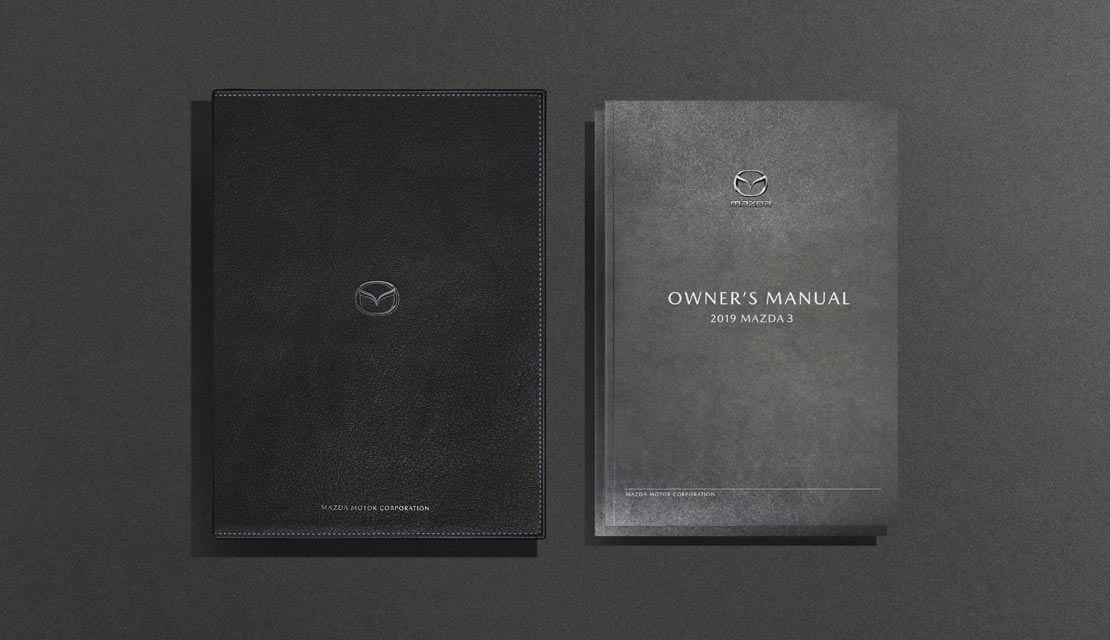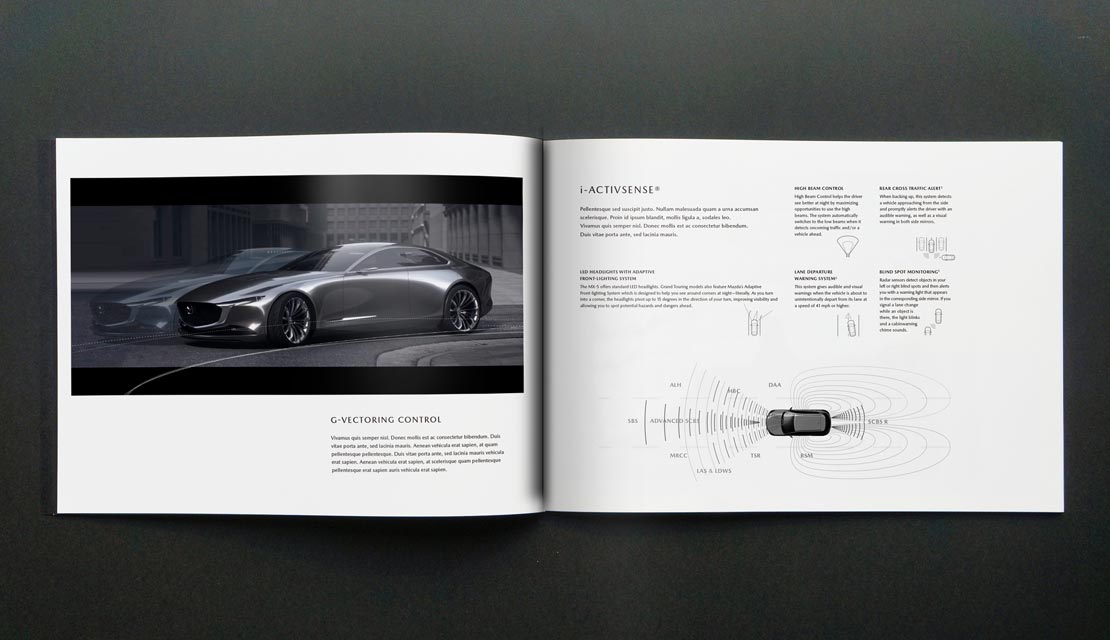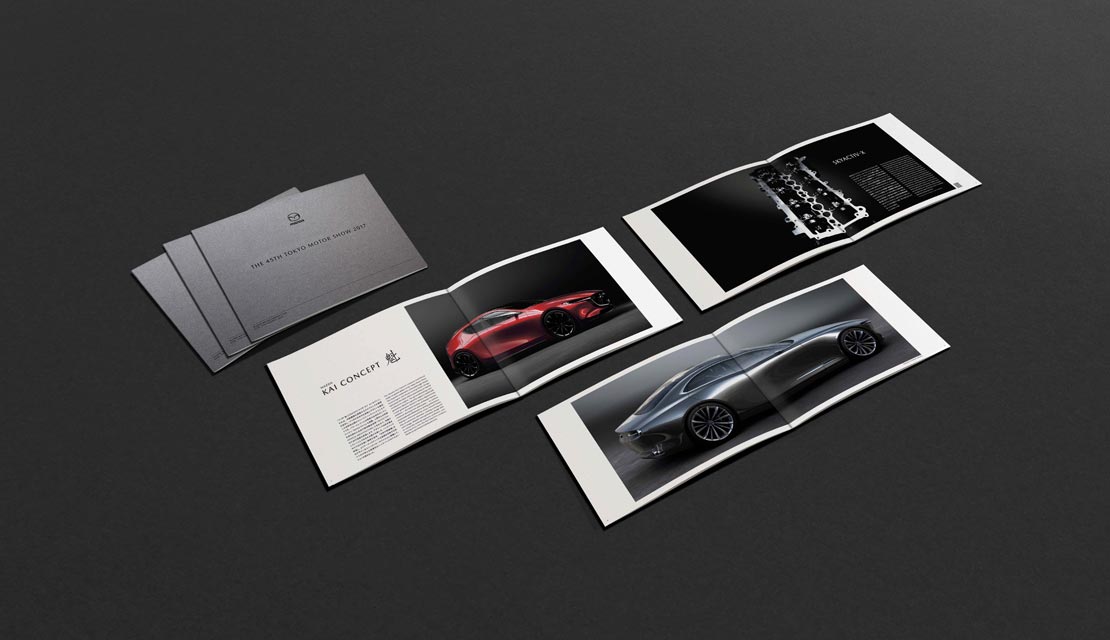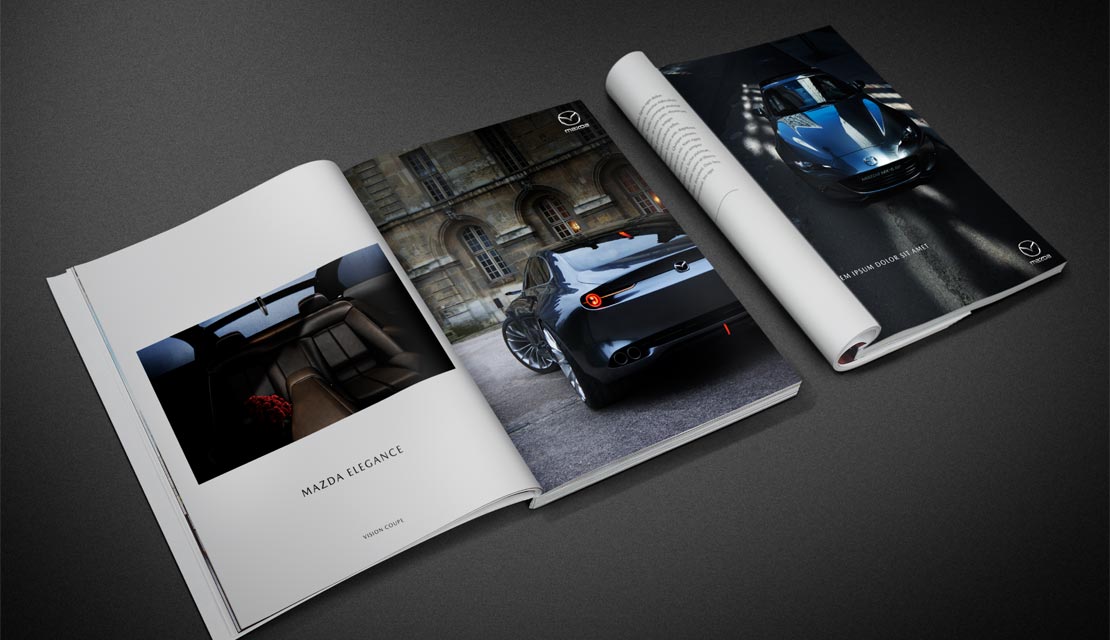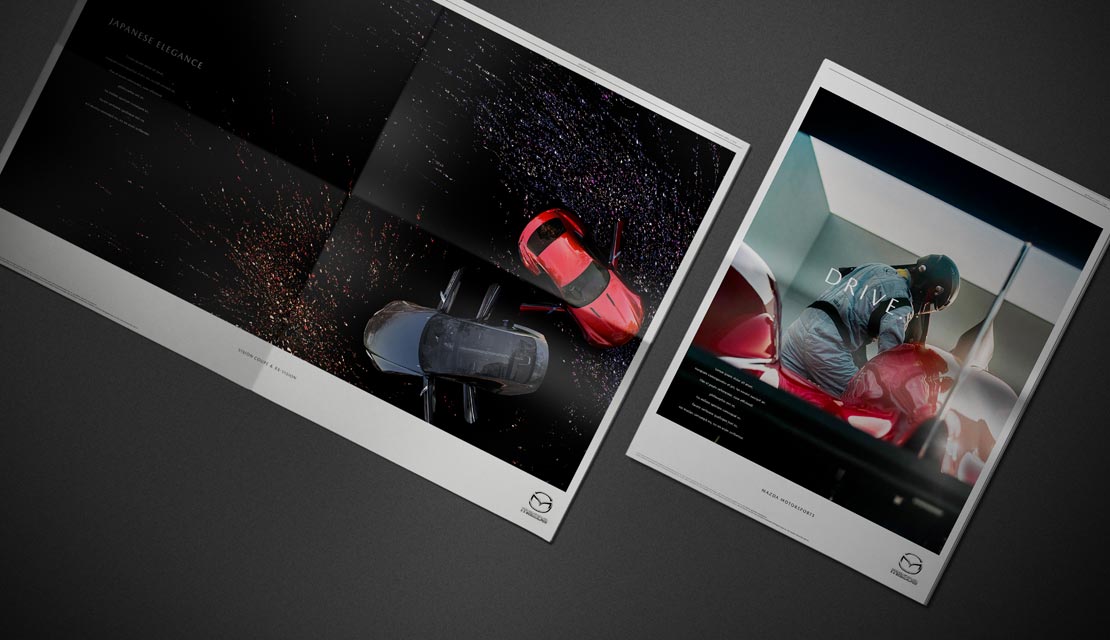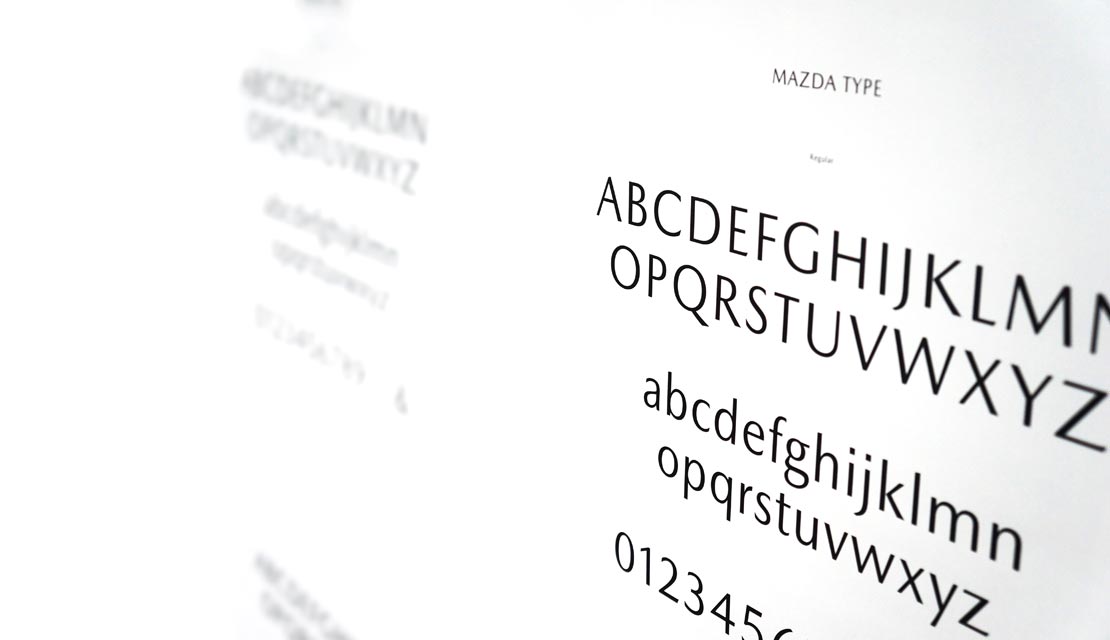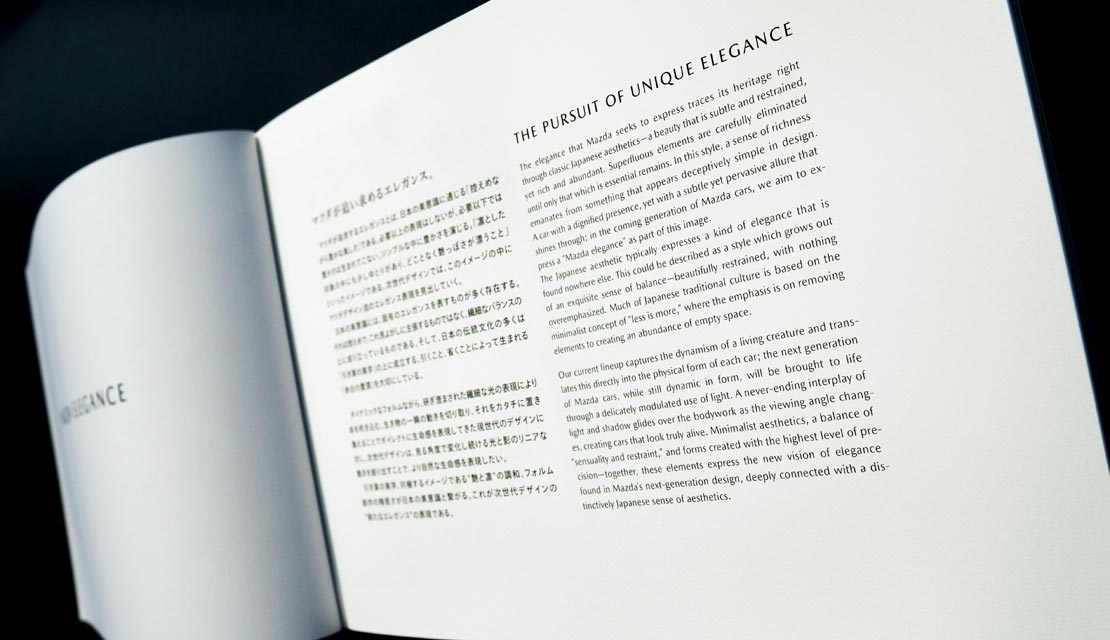
Neue Typografie bei Mazda
Gemeinsam mit Monotype Type Director Akira Kobayashi hat der japanische Autobauer Mazda eine neue Hausschrift entworfen. Durch den neu geschaffenen Brand Style soll über Grafik- und Event-Design sowie Fotografie ein einheitliches Markenerlebnis vermittelt werden.
Ziel bei der Umsetzung war es, die Arbeit menschlicher Hände in den Vordergrund allen Schaffens zu stellen und die Formsprache der Automobile in der Typografie aufzugreifen. Für das warm wirkende Aussehen der neuen Mazda-Typo ist Akira Kobayashi bei seinen Ausarbeitungen präzise ins Detail gegangen. Grundlage der Schrift sind die handgeschriebenen Buchstaben des Designers.
»Die Schrift „Mazda Type“ besitzt eine authentische Struktur mit moderner und deutlicher Form. Sie hat einen handschriftlichen Charakter, um ein Gefühl von emotionaler Wärme zu erzeugen. Ein Beispiel anhand des großen Buchstaben „M“: wie bei unseren Autos ist die obere Proportion kleiner und eleganter, was ein Gefühl von Stabilität in der Basis schafft,« erklärt Jo Stenuit, Design Director Mazda Research & Design Centre (Oberursel) die neue Typografie.